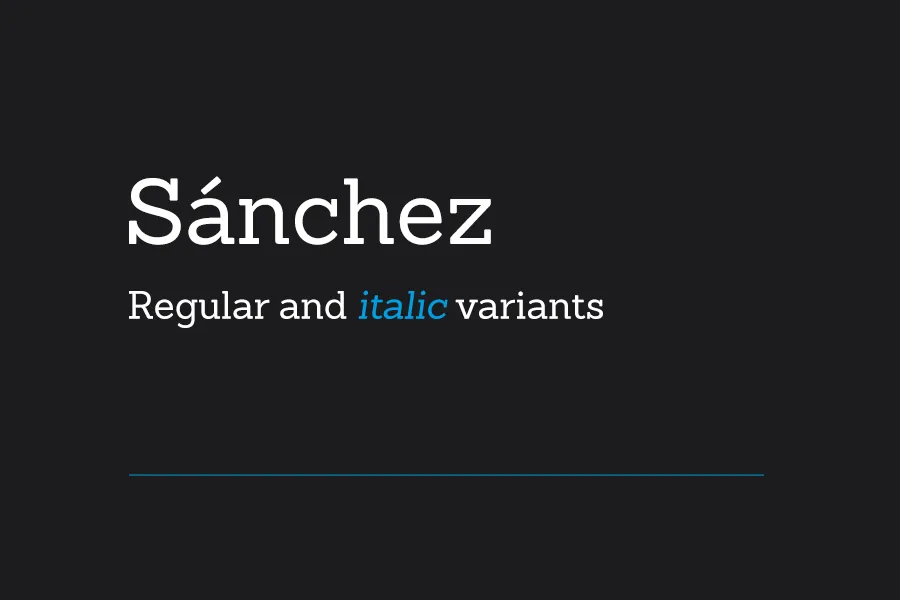
Sánchez é uma tipografia serif que se enquadra no estilo slab serif ou Egípcio, famoso por sua forte semelhança ao Rockwell. Entretanto, Sánchez apresenta um aspecto mais suave e acentuado graças às bordas redondas que adicionam contraste e equilíbrio à estrutura retangular do Rockwell. Este conjunto de caracteres sofisticados oferece uma alternativa elegante para quem busca a rígida simetria do Rockwell, mas sem perdê-lo completamente. Com seu design cuidadosamente desenvolvido por Hamilton, Sánchez é perfeito para adicionar um toque personalizado à sua tipografia, proporcionando uma versão mais suave e delicada de estilos tradicionais como o famoso Rockwell.